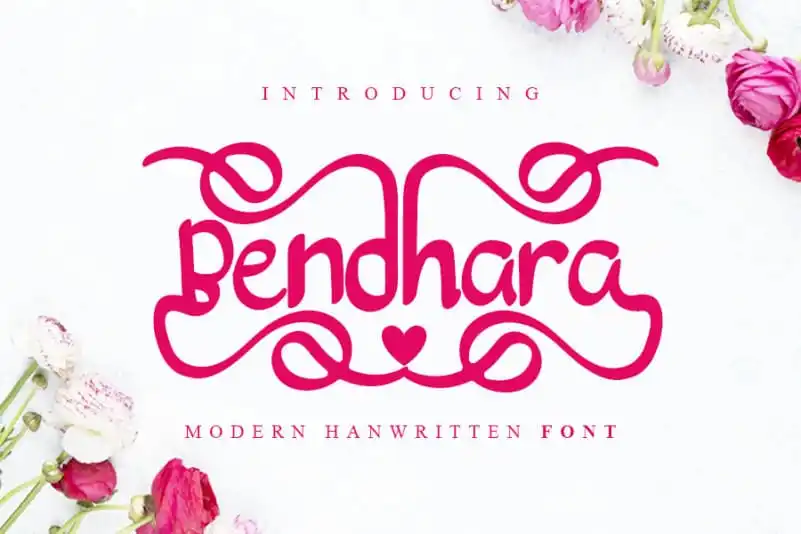
Bendhara Script Font – Fonte Grátis
Bendhara Script Font
A Bendhara Script Font é uma excelente escolha para quem busca uma fonte que se integre perfeitamente com a atualidade sem perder sua elegância clássica. Isso ocorre graças à influência do calligrafismo que mantém o design tradicional, enquanto se apresenta de forma contemporânea e moderna. Suas capacidades versáteis tornam-na uma opção perfeita para os criativos ideias – seja para letras em cartões ou títulos em envelopes ou papelaria. Esta fonte é ideal para designers que querem explorar diferentes maneiras de expressar suas ideias, garantindo assim um resultado que reflete sua personalidade única e a tradição do calligrafismo tradicional.